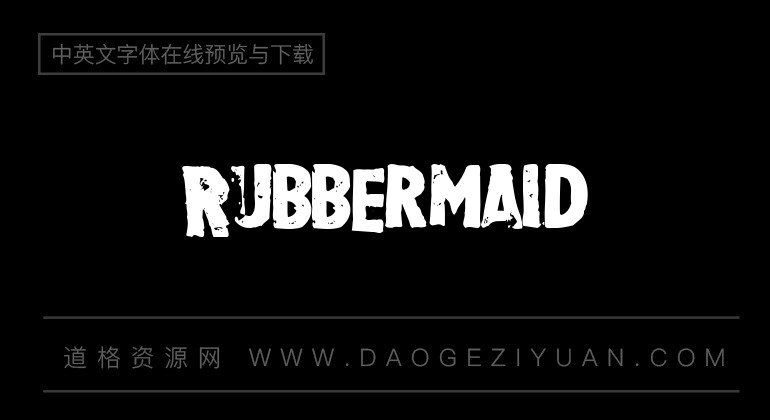
Rubbermaid
Rubbermaid是一款由Font Bureau设计的英文字体,它具有细节丰富的外观,具有较强的视觉冲击力,非常适合用于广告和海报的设计。它采用了细节丰富的英文字体,让文字更加突出,更有吸引力。同时,它还拥有更多的字形,可以满足不同的设计需求。
Rubbermaid是一款非常不错的手写艺术字体,具有很好的视觉感,适合于文化类的宣传设计、商业类品牌的广告和产品包装设计以及个性化文字排版等较多场景。